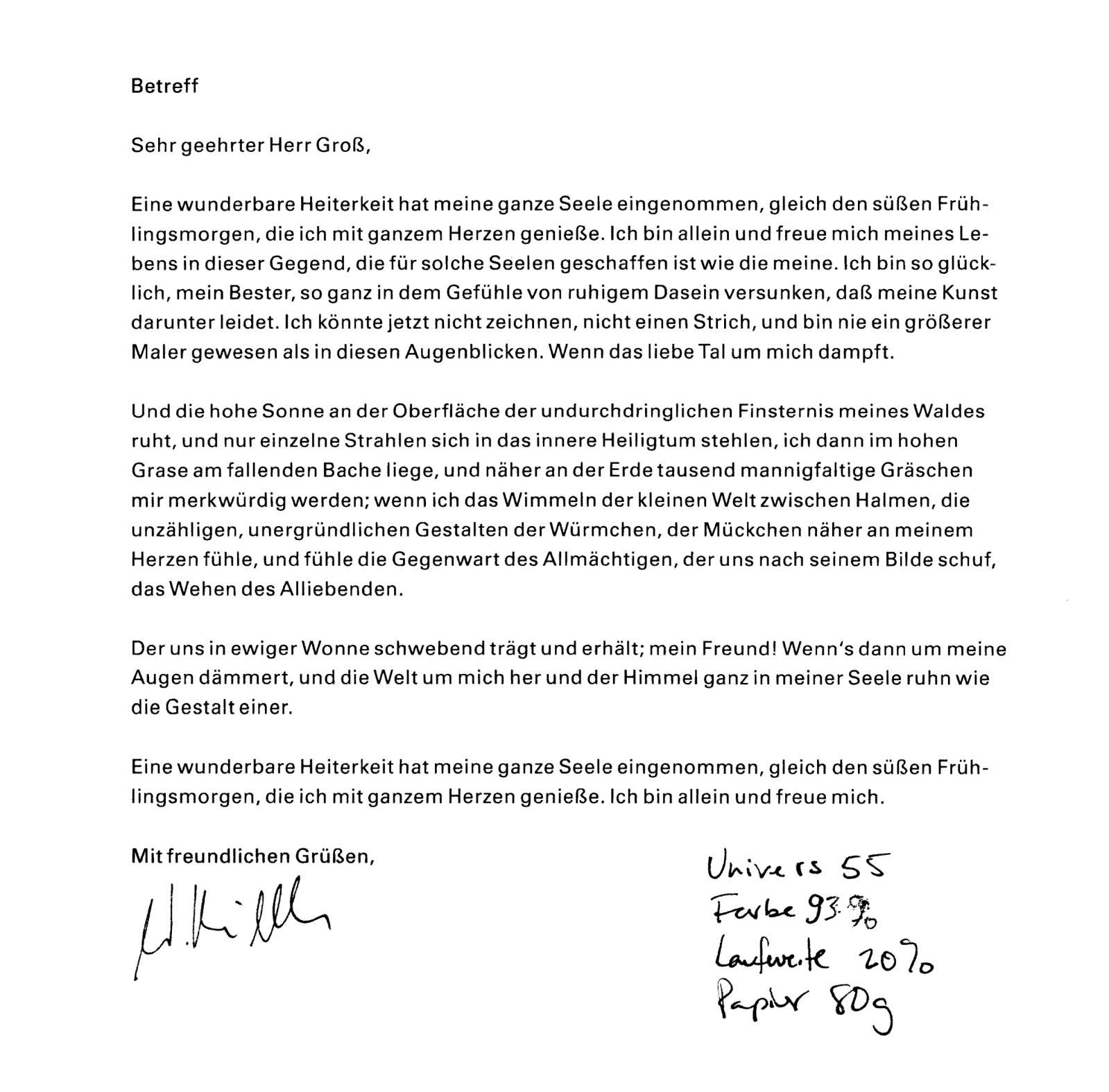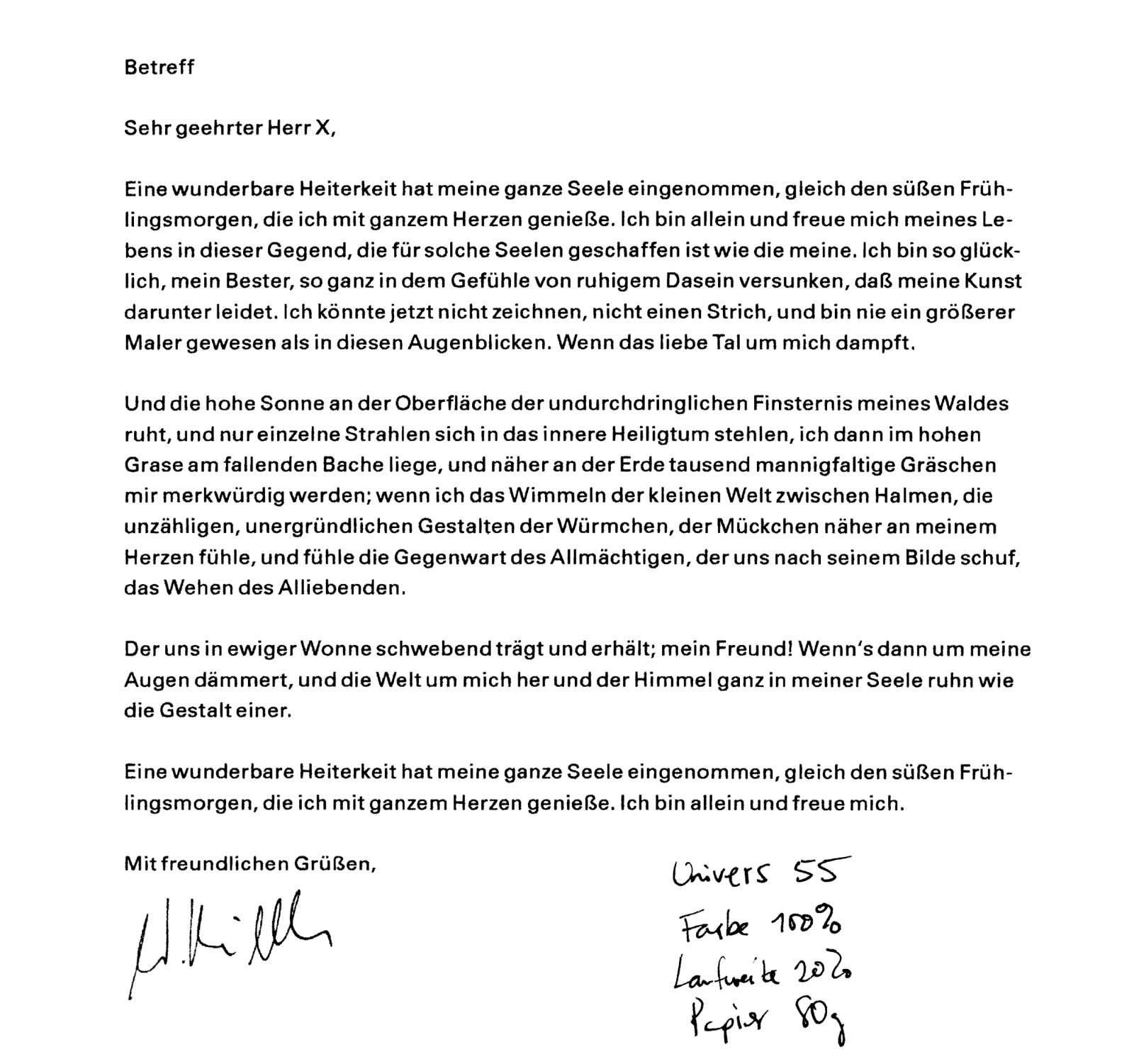
Linotype Univers® 430 Basic Regular vs Univers Next Pro
ich wollte generell fragen, ob einen Unterschied (Qualität?) besteht zwischen
Linotype Univers® 430 Basic Regular
Univers Next Pro Regular
das ist eine berechtigte frage. nach einem kurzen blick auf die linotype-seite ist mir das auch nicht recht klar. theoretisch sind die next-versionen neu gezeichnete oder zumindest grundlegend überarbeitete fassungen existierender schriften. ich kann aber zwischen der linotype univers (überarbeitung der original-univers von 1997) und der univers next, zumindest anhand der online-schriftmuster, keine gravierenden unterschiede entdecken. ein paar sonderzeichen (wie @) sind anders, okay – aber sonst?
anders als zu den anderen next/nova-veröffentlichungen ?nde ich zur univers next auch so gut wie kein informationsmaterial online. das ist auffällig. falls darüber jemand mehr weiß, möge er sein wissen mit uns teilen. jetzt interessiert es mich auch.
die Frage kam, weil ich die Univers 55 für meine Hausschrift gewählt habe. Dann habe ich gesehen, dass es Univers Next Pro 430 (388 Zeichen) und Linotype Univers 430 (669 Ziechen) gibt. Nun bin ich verwirrt, welche ich nehmen soll ...
zwischen der univers (ohne ›linotype‹) und den anderen beiden besteht de?nitiv ein mit dem bloßen auge erkennbarer unterschied. bei der überarbeitung 1997 wurden unter anderem schnitte hinzugefügt sowie die gewichte untereinander harmonisiert. die neue regular ist leichter, weil es jetzt eine medium gibt, die die lücke zur recht massiven bold füllt. zudem ist die neue version von 1997 etwas kontrastreicher und feiner gezeichnet. zum vergleich:
inzwischen habe ich auch herausgefunden, was es mit den 388 und 669 zeichen auf sich hat. die univers next enthält – tada! – kapitälchen und mediävalziffern (dass sie damit nicht werben bei linotype?!). trotzdem ist die univers next pro sowohl als einzelschnitt wie auch im paket nicht teurer als die linotype univers. ein weiterer unterschied zwischen der 1997er linotype univers und der univers next besteht darin, dass letztere laut website »optimiert für die Darstellung gut lesbarer Schriften auf Computer-Bildschirmen« ist, also wahrscheinlich besser gehintet.
wenn es dir um typogra?sche feinheiten und die bestgezeichnete fassung geht, kommst du an der univers next nicht vorbei. die prä-1997er univers ist demgegenüber doch eher plump und schlecht ausgebaut, dafür aber sehr viel günstiger. wenn du keinen großen zeichensatz sowie keine kapitälchen brauchst und auf die schöneren kurven pfeifst, zahlst du für den billigsten schnitt (truetype oder postscript) knapp 29 euro statt über 82 euro für die univers next. selbst mit pro-zeichenbelegung ist die alte univers nicht viel mehr als halb so teuer wie die neue (42 euro). von letzterem rate ich aber ab; die diakritika der univers next sind teilweise besser gelungen. wenn es schon pro sein muss, dann auch richtig.
vorausgesetzt, dass es nicht am geld mangelt, würde ich also die univers next nehmen. diese schrift mit kapitälchen und mediävalziffern einzusetzen, könnte eine ganz ungeahnte wirkung haben. früher war es ja quasi ein markenzeichen der statischen groteskschriften wie akzidenz-grotesk, helvetica und eben univers, solche kinkerlitzchen gleich gar nicht anzubieten. vielleicht hat hier ja jemand die schrift und kann mal ein paar zeilen damit zeigen?
Soweit ich das in Erinnerung habe (ich habe eine umfangreiche Univers Next Infobroschüre zu Hause stehen ...), ist es so:
Univers / Univers LT / ...:
Alte Digitalisierung des Originals, verhältnismäßig schlecht ausgebaut, mit zweistelliger Nummerierung (Regular = 55)
Linotype Univers Next:
Eine deutliche Überarbeitung / Neuentwurf, ohne Anspruch auf volle Authenzität. Also so, wie Frutiger die Univers "heute gemacht hätte", Brücken nach hinten abgebrochen. Hier ist das neue Nummernsystem mit 3 Stellen eingeführt worden (Regular = 430)
Was nun aber die "Linotype Univers" mit 3stelliger Nummerierung ist ... das kann ich leider auch nicht beantworten. Vielleicht eine "Original-Univers" mit dezenter Überarbeitung und neuer Nummerierung?
Die Zusätze Pro, Office, etc. sind dann Hinweise auf Umfang des Zeichensatzes, Stylelinking für Officeprogramme, Bildschirmoptimierung, etc.
ich werde mich wohl für die Univers Next Pro Reihe entscheiden.
Zum selben Thema Univers, die Univers 55 schein mir recht schwer/schwarz. Deshalb habe ich die Tonwert in InDesign auf 93% reduziert, denn das Schwarz schien mir doch zu kräftig. Alternative war ein Univers 45. Kennt jemand dieses Problem?
Linotype Univers Next:
Eine deutliche Überarbeitung / Neuentwurf, ohne Anspruch auf volle Authenzität. Also so, wie Frutiger die Univers "heute gemacht hätte", Brücken nach hinten abgebrochen. Hier ist das neue Nummernsystem mit 3 Stellen eingeführt worden (Regular = 430)
Univers 55 bei 93 bei 600 dpi auf 80 g
Zugegeben da geht was vorleren bei s/w Datei, aber wenn man es ausdruckt sieht 100% schwarz eben etwas fett/schwer, meiner Meinung nach.